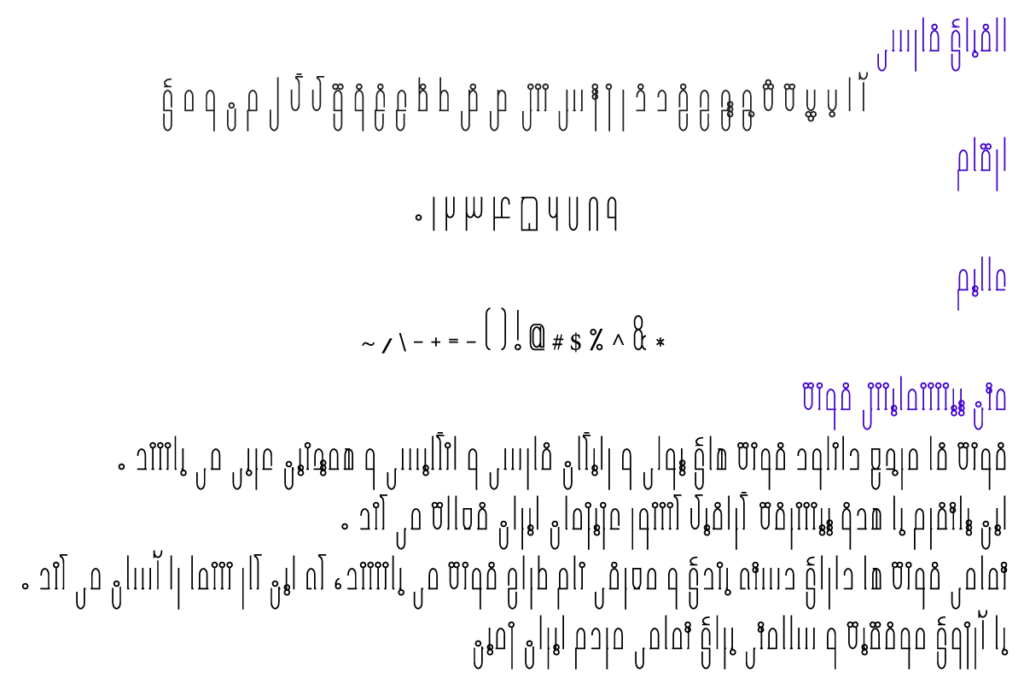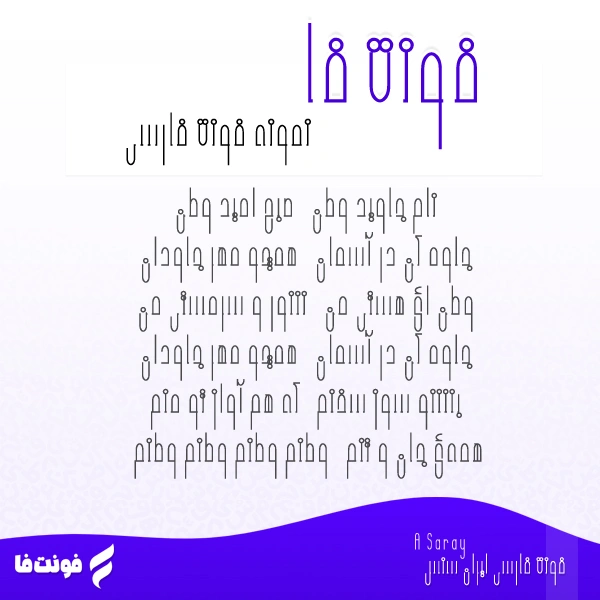
فونت فارسی سارای – A Saray
نوع فونت: فونت گرافیکی
توضیحات و معرفی فونت سارای
فونت فارسی سارای ( A Saray ) از مجموعه فونت های آزاد می باشد، همینطور نوع فونت گرافیکی می باشد.
فونت زیبای مرتبط در سال 1393 طراحی و ساخته شده است.
در تصویر زیر می توانید شعر زیبای «وطنم» را که با این قلم نوشته شده، تماشا کنید.